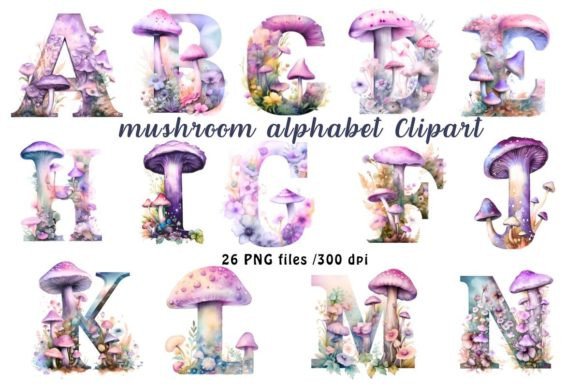
Watercolor Letters Mushroom Clipart
Jeśli szukasz wysokiej jakości materiałów, takich jak Watercolor Letters Mushroom Clipart, ten pakiet premium to fantastyczny wybór dla Twoich kreatywnych projektów.